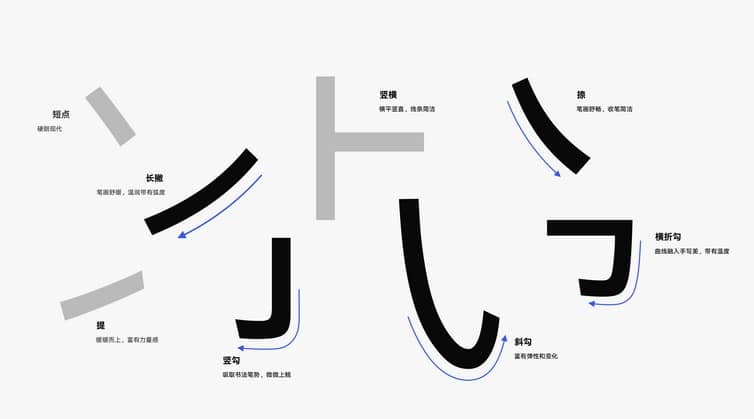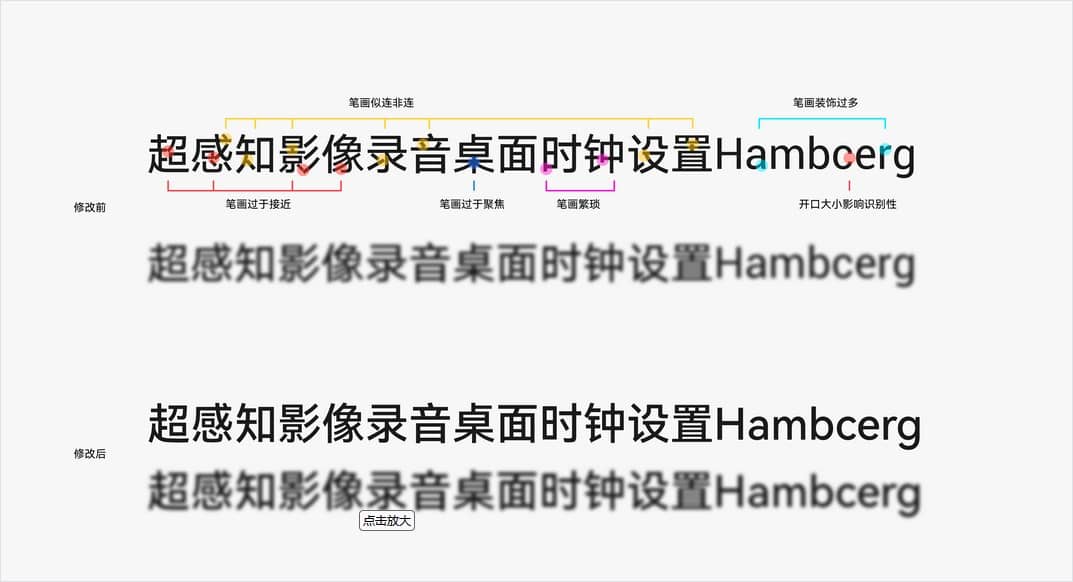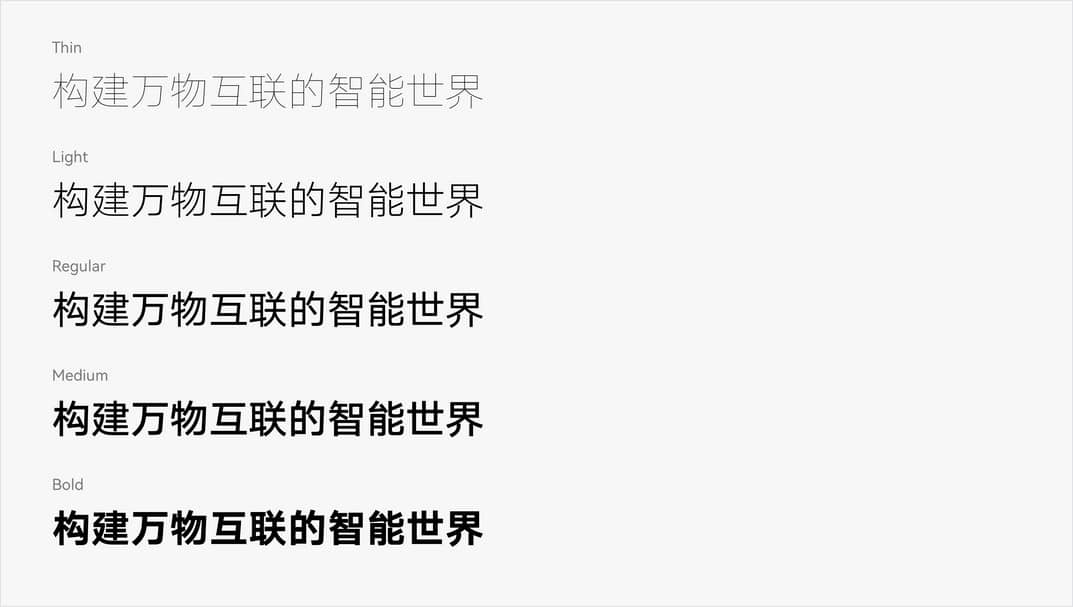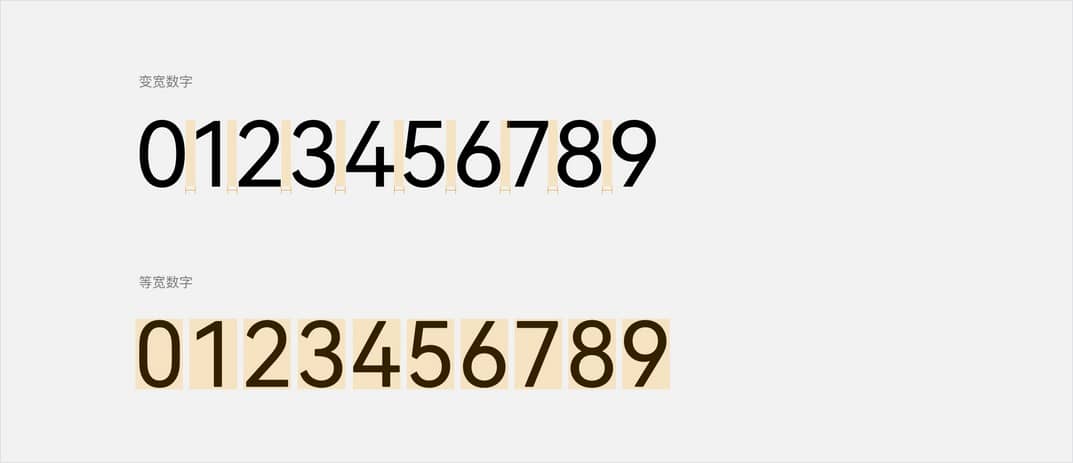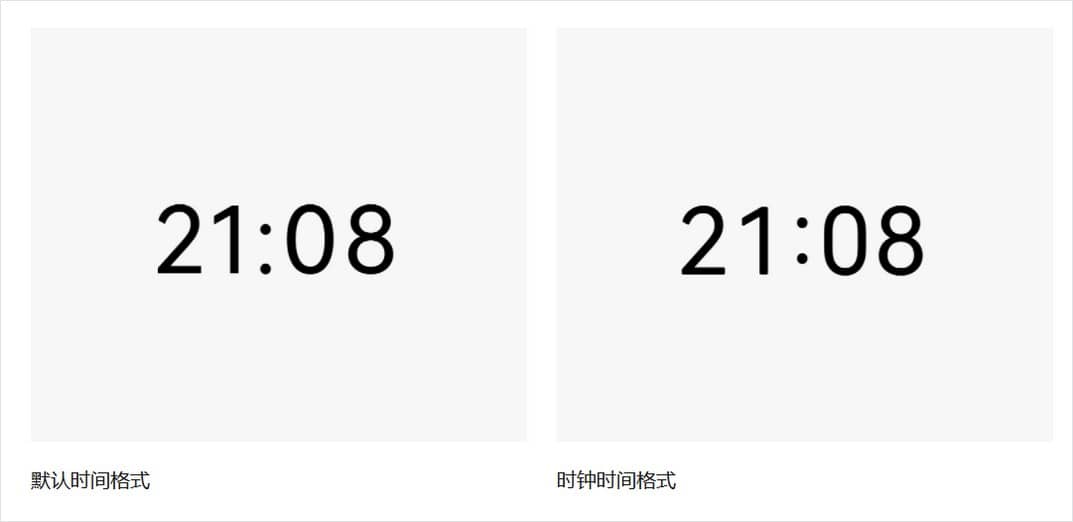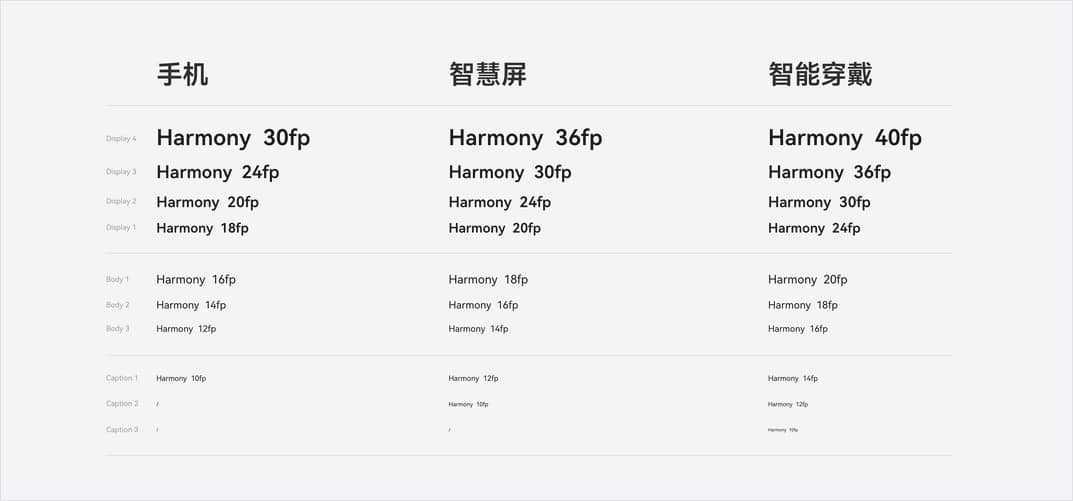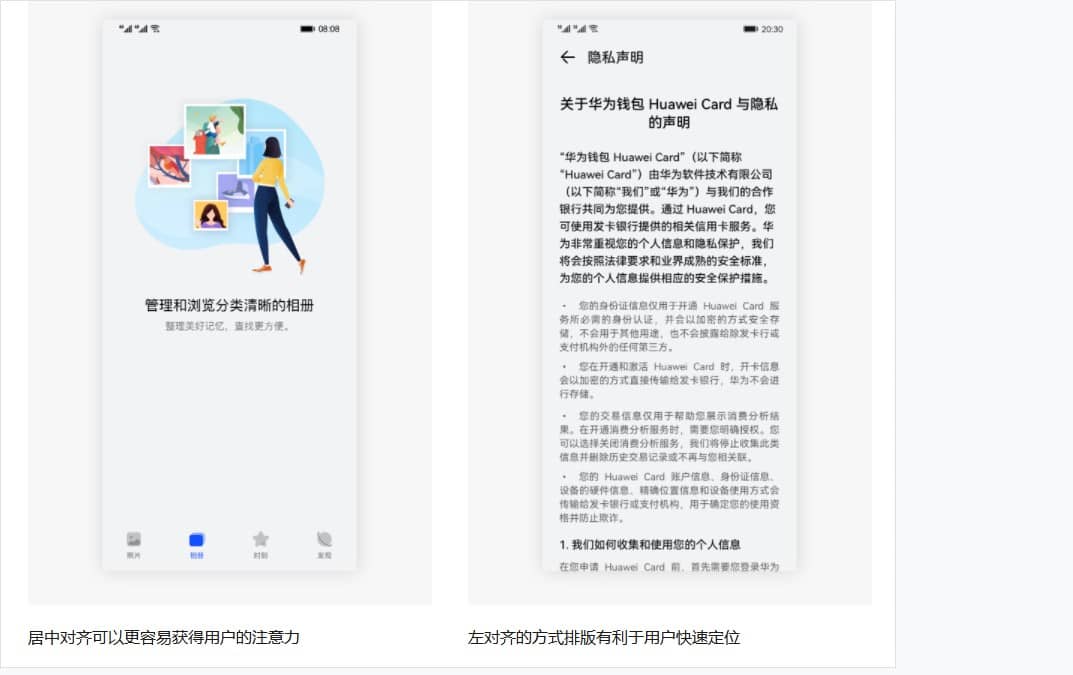
一款多语言的无级可变字体:鸿蒙 HarmonyOS Sans
华为鸿蒙字体 (HarmonyOS Sans),华为定制字体,为鸿蒙OS一同上线,于2021年6月发布上线,可以免费商用。设计上聚焦于功能性、普适性,是一款多语言的无级可变字体,该字体支持简体中文、繁体中文、拉丁、西里尔、希腊、阿拉伯等5大书写系统,105种语言全球化覆盖。
通过研究用户在不同场景下对多终端设备的阅读反馈,综合考量不同设备的尺寸、使用场景等因素,同时也考虑用户使用设备时因视距、视角的差异带来的字体大小和字重的不同诉求,华为为 HarmonyOS 设计了全新系统默认的字体——HarmonyOS Sans,该字体拥有以下特性:
易读:中文笔画复杂,HarmonyOS Sans在设计时为应对可变字体笔画连接处易破碎的情况,做出优化统一处理,使得字体最终呈现效果干净而利落。
独特:HarmonyOS Sans字体笔画优化,削弱了黑体的机械感;采用现代感结构处理;笔画造型融入了书写美感。
通用:HarmonyOS Sans字体比Roboto更显大更显宽,与中文匹配度更高,同时对符号设定了多种与文字相匹配的排版属性;在深色模式下使用了更细的字重,让字体的视觉粗细与浅色模式保持一致。
字体风格
全新字体笔画设计
在保障字体体验的功能性前提下,我们在人文和现代中找到新的平衡。在短笔画时保持横平竖直,简约无装饰,撇捺弯钩长笔画中融入书法的笔势美学,带来全新的视觉感受。
优化字体灰度,提升阅读体验
在不同设备的应用场景下,字体的灰度会影响在弱光环境、小字号、远距离下的识别性。因此我们优化字体的灰度,让新字体在不同场景下具有更好的识别性和阅读体验。
统一多语言字形风格
我们重新设计了中文、拉丁文、希利尔文、希腊文、阿拉伯文的字形样式,支持100+语言,让多语言下阅读体验更加一致。
动态字重粗细调节
HarmonyOS Sans支持可变特性,让用户选择他们喜欢的字体粗细来进行文本的显示。
支持更多字重能力
HarmonyOS Sans增加了Thin、Light、Bold、Black的字重能力,开发者可以选择需要的字重来构建界面的信息层级。
等宽与变宽数字字体
HarmonyOS Sans支持变宽和等宽两种样式。文本混排中使用系统默认的变宽数字,在阅读文本段落中能让阅读体验更加连贯。而等宽时钟数字在需要强调数值以及数据需要经常变化的表格和时钟数字的场景中使用时,可以保持数字字宽的对齐,同时更具图形化的呈现可以在界面中脱颖而出。
支持时钟字体特性
HarmonyOS Sans支持时钟字体特性,冒号格式会根据时间格式自动调整位置。
多设备字号层级
选择合适的字号有助于定义内容的信息层级,以及达到内容的可读性。通过研究全场景设备的显示环境、用户使用时环境的差异,我们为不同设备形态定义了一套构建信息层级的字号系统。
文本对齐规则
不同的文本对齐方式可以引导用户的视觉流向。在段落文本中文本超长换行默认使用左对齐的方式,因为人的浏览视线都是从左往右移,因此大段需要阅读的文案,采用左对齐的方式排版有利于用户快速定位,保证良好的阅读体验。相对于更常见的左对齐,居中对齐可以更容易获得用户的注意力,因此在标题上、空页面的描述文本以及在插画的引导页上使用居中对齐可以更有效地抓住用户眼球。